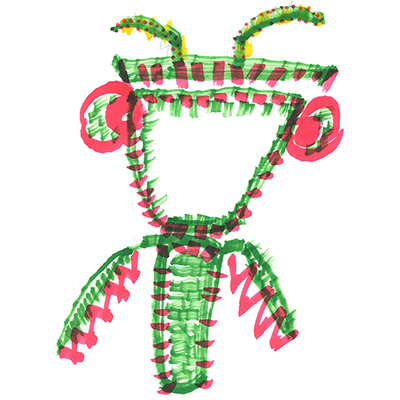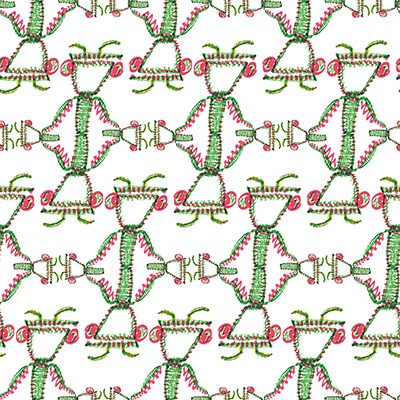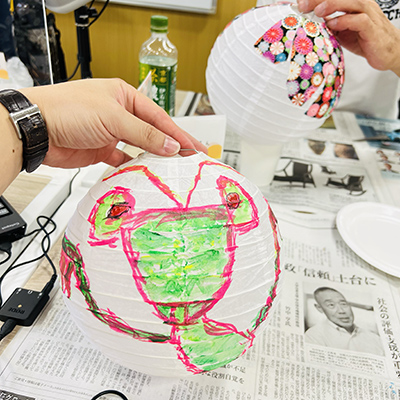
カマキリ立ちはだかる
昆虫界最強が立ちはだかる
ご存知通りの、蟷螂にちなみカマキリです。イラレ作業で言えばカマキリの分割?パターン作成かな?見たイメージです。後から思う事、鼻がないカマキリには鼻があったかしら・・?(姫蟷螂)
昆虫界最強と言われるカマキリが手を組んで立ちはだかる。怖いものなし。いかなる敵からも身を守る強い意志を表現。(乙牧 和宏)
昆虫界最強と言われるカマキリが手を組んで立ちはだかる。怖いものなし。(株式会社テクノヒューマンキャピタルラボ)